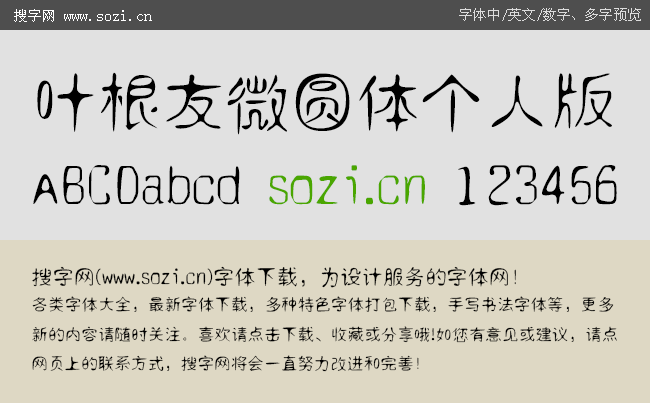
葉根友微圓體個(gè)人版
搜字網(wǎng)提供一款葉根友微圓體個(gè)人版中文字體下載。葉根友微圓體個(gè)人版是一款藝術(shù)型字體,該字體線條細(xì)膩,有點(diǎn)類似于毛筆字跡,字形圓潤有個(gè)性,能夠適用于包裝印刷、廣告設(shè)計(jì)、平面設(shè)計(jì)、書籍報(bào)紙等領(lǐng)域使用。